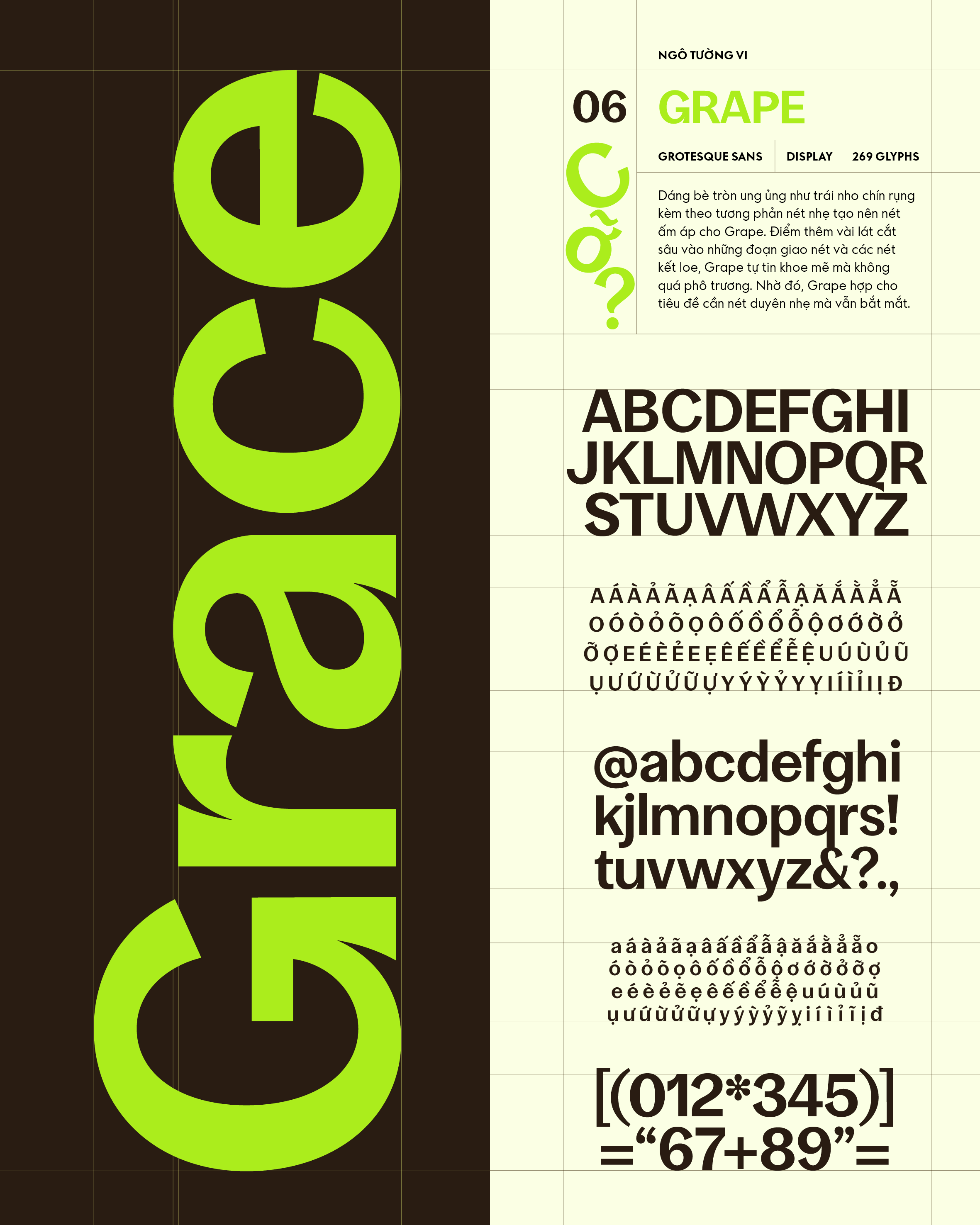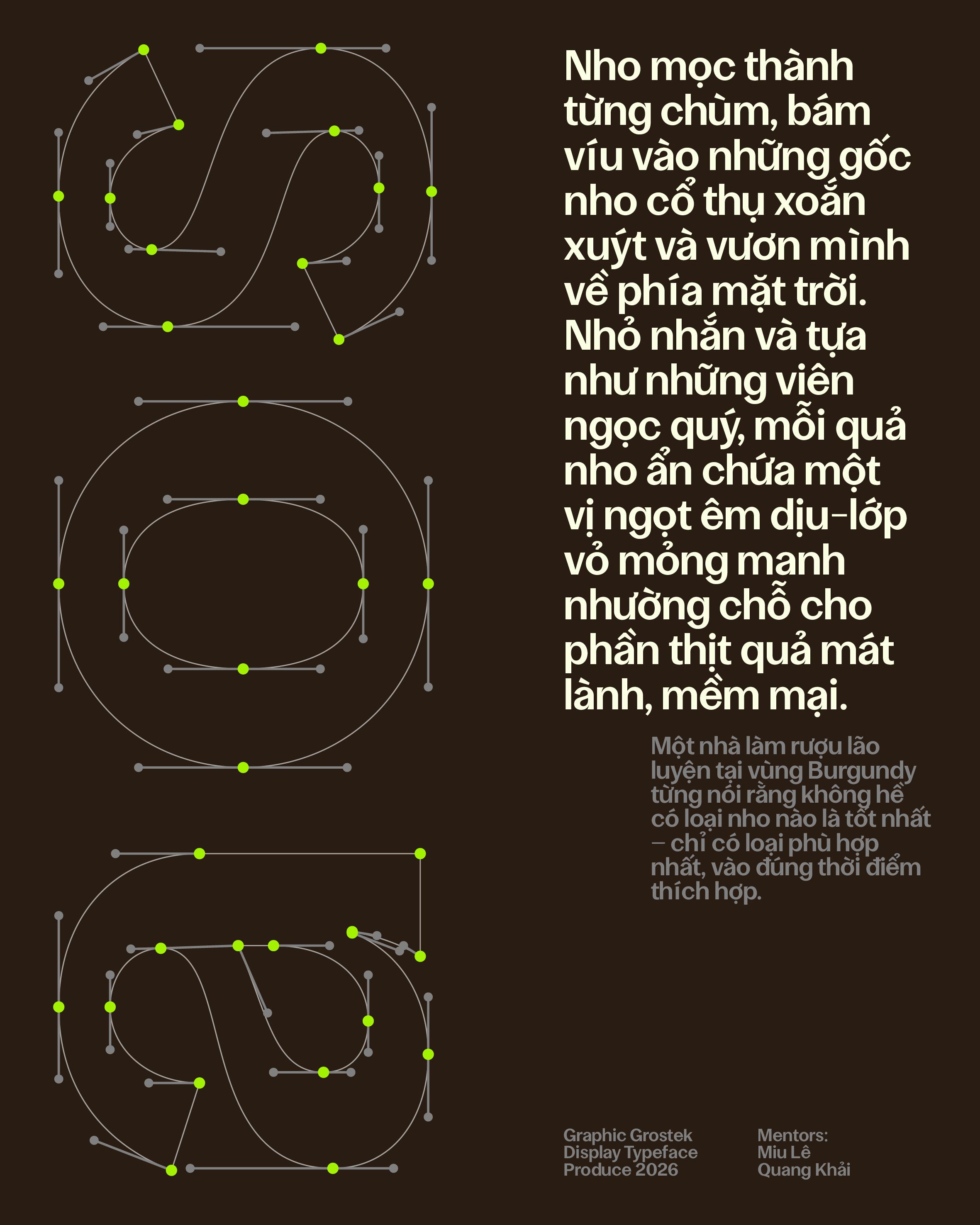
Grape
Về Grape: Dáng bè tròn ung ủng như trái nho chín rụng kèm theo tương phản nét nhẹ tạo nên nét ấm áp cho Grape. Điểm thêm vài lát cắt sâu vào những đoạn giao nét và các nét kết loe, Grape tự tin khoe mẽ mà không quá phô trương. Nhờ đó, Grape hợp cho tiêu đề cần nét duyên nhẹ mà vẫn bắt mắt.
Grotesk Sans-serif
Display
Ngô Tường Vi